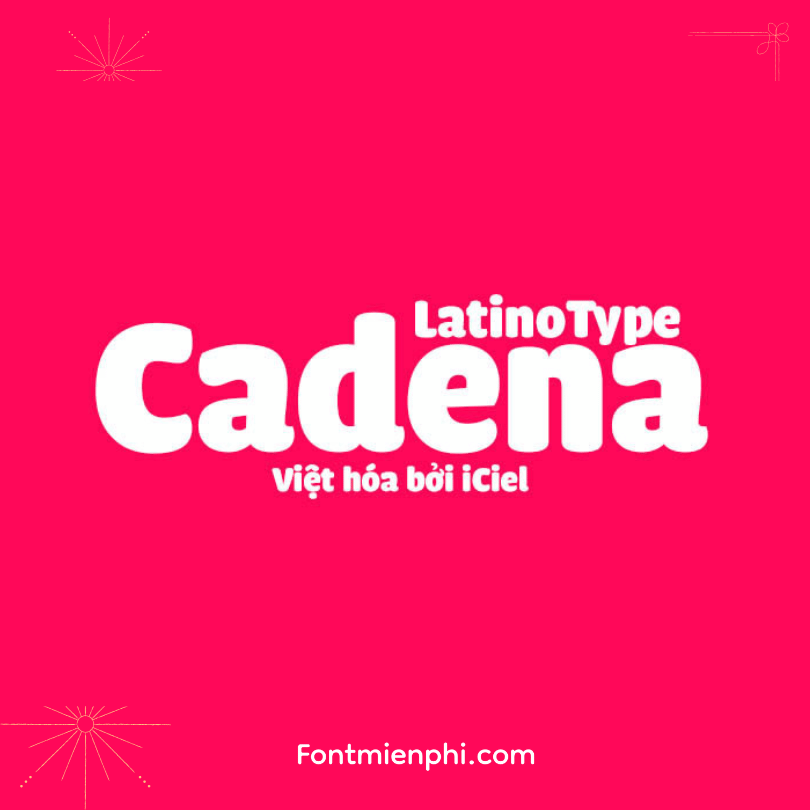
Việt hóa font iCiel Cadena
Font iCiel Cadena là một trong những font chữ hiện đại và độc đáo, được thiết kế với phong cách thanh thoát, dễ đọc. Việc Việt hóa font này không chỉ giúp người dùng Việt Nam tiếp cận dễ dàng hơn mà còn nâng cao trải nghiệm sử dụng cho các dự án thiết kế, in ấn hay website.
Việt hóa font iCiel Cadena bao gồm việc chỉnh sửa và bổ sung các ký tự tiếng Việt như á, à, ả, ã, ạ, và các dấu thanh khác. Điều này giúp font trở nên hoàn thiện hơn cho ngôn ngữ tiếng Việt, giữ nguyên vẻ đẹp và phong cách của font gốc.
Sử dụng font iCiel Cadena sau khi được Việt hóa mang lại sự chuyên nghiệp cho các sản phẩm thiết kế, từ bìa sách, poster đến giao diện trang web. Font này phù hợp với nhiều lĩnh vực như thời trang, nghệ thuật, giáo dục và kinh doanh, tạo điểm nhấn nổi bật và thu hút sự chú ý của người xem.
Việc áp dụng font iCiel Cadena vào thiết kế không chỉ giúp thể hiện thông điệp một cách rõ ràng mà còn góp phần tạo nên bản sắc riêng cho thương hiệu. Hãy thử nghiệm ngay font iCiel Cadena đã được Việt hóa để làm mới phong cách thiết kế của bạn và thu hút khách hàng một cách hiệu quả nhất.